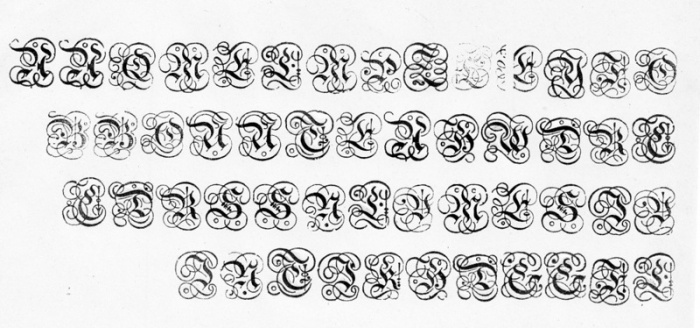
ich habe eine Frage an die Fachleute für alte Bleischriften.
Ich habe eine kürzlich einen Satz von 50 Typen bekommen,
über die ich gern mehr wissen würde:
1. Wie heißt diese Schrift?
2. Aus welcher Zeit stammt sie?
3. Da ich bisher nur ca. 80% des Alphabets identifiziert
habe, suche ich jemanden, der mir die Typen ordnet.
1. Keine Ahnung, aber es sind Zierintialien.
2. Angesichts der Tatsache, dass keine Umlaute enthalten sind und kein getrennter Buchstabe für I und J enthalten ist (hier musst Du wissen, inwiefern Du davon ausgehst, ein vollständiges Alphabet erhalten zu haben), ist eine Entstehung nach 1900 unwahrscheinlich (aber nicht unmöglich).
3. Unter der Annahme, dass jeder Großbuchstabe (außer X) in genau einer Form enthalten ist und über das Ausschlussverfahren würde ich sagen:
A A Q M E L M P Z L? E Y F O
B B O U U T E A H W D R C
C D R S S N L V M E S J V
J N T J K H D G G F L
Sind das wirklich gegossene Bleilettern oder vielleicht aufgeklotzte Klischees? Zierinitialen wurden nämlich auch gern als Klischees hergestellt und dann dürfte eine Identifizierung noch schwerer als sowieso fallen.
Hilfreich wäre auch die Auskunft - falls es Bleilettern sind - ob es sich um Monotype- oder Komplettguß handelt. Monotypeguß hat eine eckige Kerbe als Signatur, Komplettguß meist eine oder mehrere auch unterschiedliche runde Kerbe(n). Vielleicht findest Du bei genauer Betrachtung an den Bleilettern auch eine sogenannte Gußmarke (ein kleines Logo oder Monogramm), die einen Hinweis auf die Gießerei geben könnte. Gußmarken waren aber meist nur an einzelnen Buchstaben und m.W. nie am kompletten Satz ...
ich kenne sie nur unter den namen dutch initials, paul lloyd hat sie mal digitalisiert:
Die Schrift ist ähnlich, aber nicht identisch. Insbesondere G, S und Z unterscheiden sich deutlich.